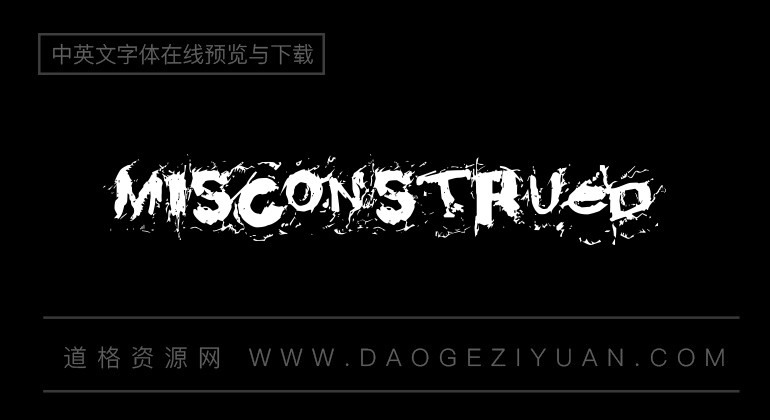
Misconstrued
Misconstrued 字体是一种手写风格的字体,由设计师 Timo Kuilder 创造。该字体的设计灵感来源于手写字体的不完美之处,如不规则线条和字母形状的变化。 Misconstrued 字体的特点是字母间距较小,字母形状不规则,笔画粗细不均匀。这些特点赋予了字体个性化和独特性,适合用于设计海报、标志、商标、网站和应用程序。 Misconstrued 字体包括正常、斜体和加粗三种字重,支持英文和拉丁语字符。它是一种免费字体,可以在多个字体网站上下载和使用。
Misconstrued是一款非常不错的手写艺术字体,具有很好的视觉感,适合于文化类的宣传设计、商业类品牌的广告和产品包装设计以及个性化文字排版等较多场景。